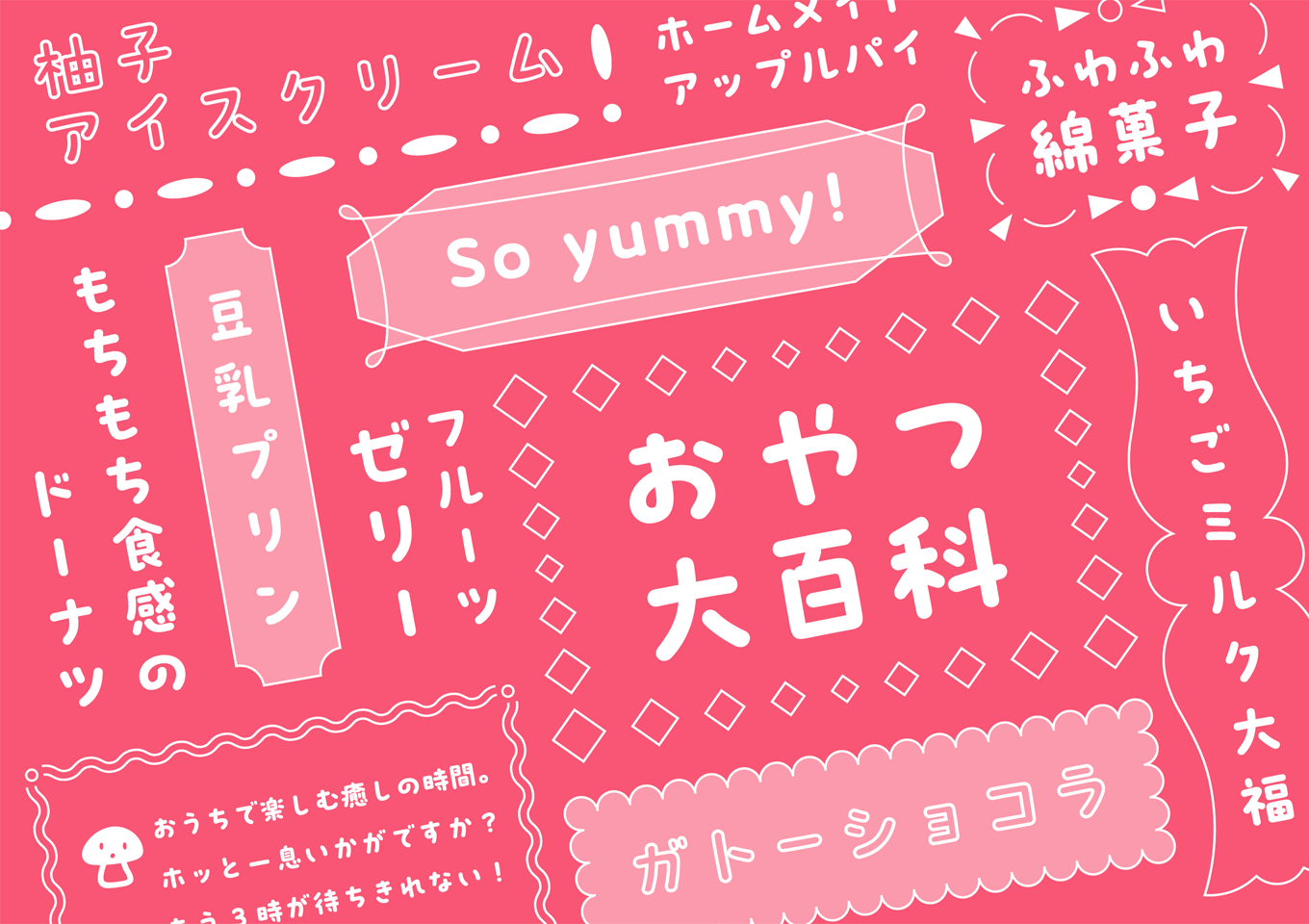
「プフ」シリーズは、統一しすぎない自由な字形と小さめの字面が特徴のデザイン書体ラインナップです。「プフ マーチ」は、丸ゴシック体風のデザインとやや幾何学的なプロポーションが特徴で、パッケージやコミックの装丁、動画テロップなどで柔らかさや親しみやすさを表現する際に最適です。また、書体のキャラクターを表すオリジナル絵文字を1文字搭載しており、異体字として選択入力が可能です。